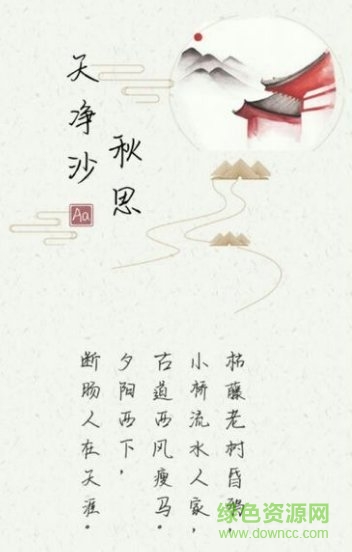
天凈沙秋思體是一款清秀質(zhì)樸的手寫(xiě)字體,隨意清揚(yáng)的筆觸融入了最原始的秋季之感,給人淡淡哀愁的觸目體驗(yàn),自己清晰而不繚亂,讓你的創(chuàng)作別有一番風(fēng)味,快來(lái)綠色資源網(wǎng)試試吧!
枯藤老樹(shù)昏鴉,
小橋流水人家,
古道西風(fēng)瘦馬。
夕陽(yáng)西下,斷腸人在天涯。
天凈沙秋思體,結(jié)合了思鄉(xiāng)之愁緒與秋季淡然之寂靜,讓文字的一張一弛間盡顯藝術(shù)本色,干凈而不拖沓、流暢而不恣意,可廣泛運(yùn)用在平面創(chuàng)作、海報(bào)設(shè)計(jì)、廣告創(chuàng)意等諸多領(lǐng)域!